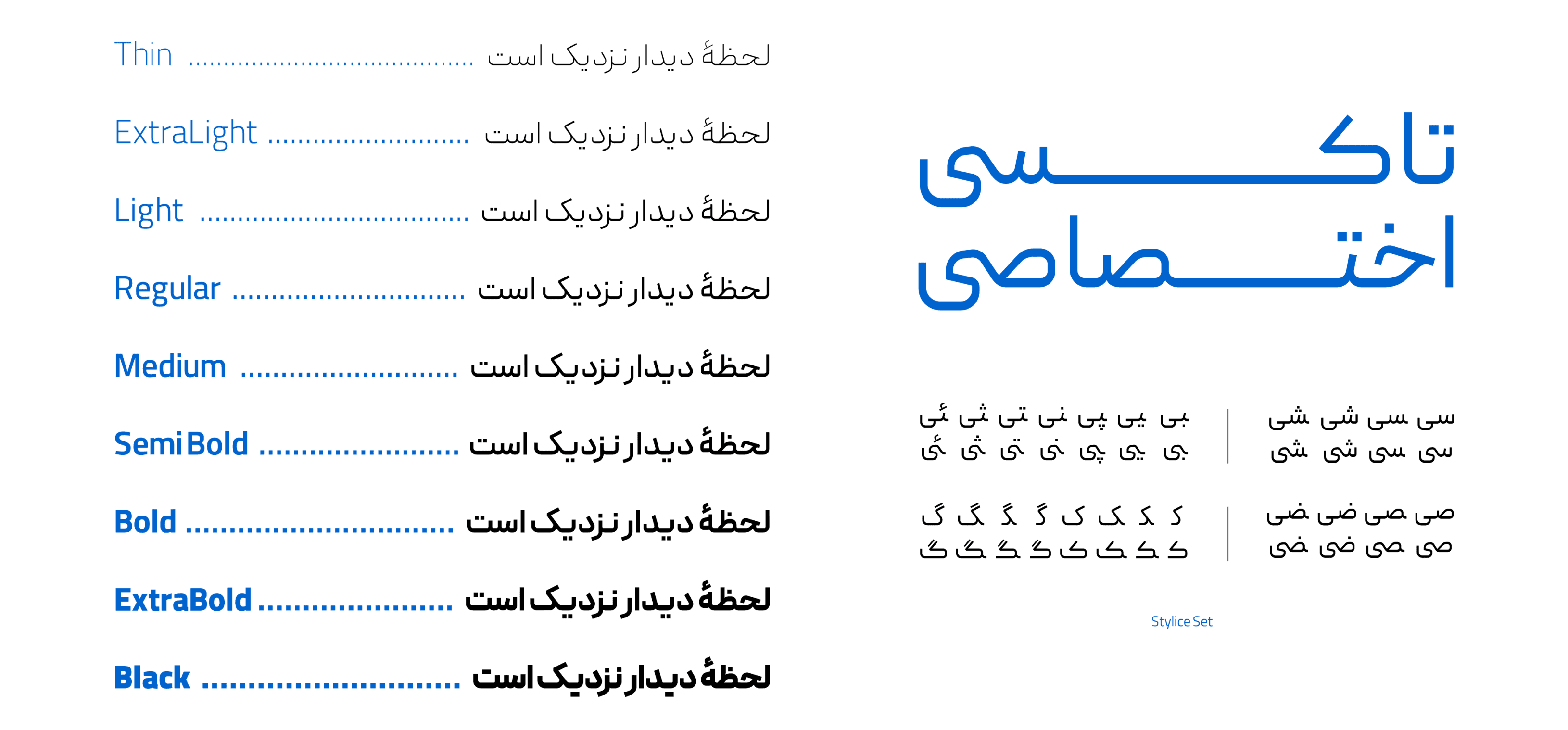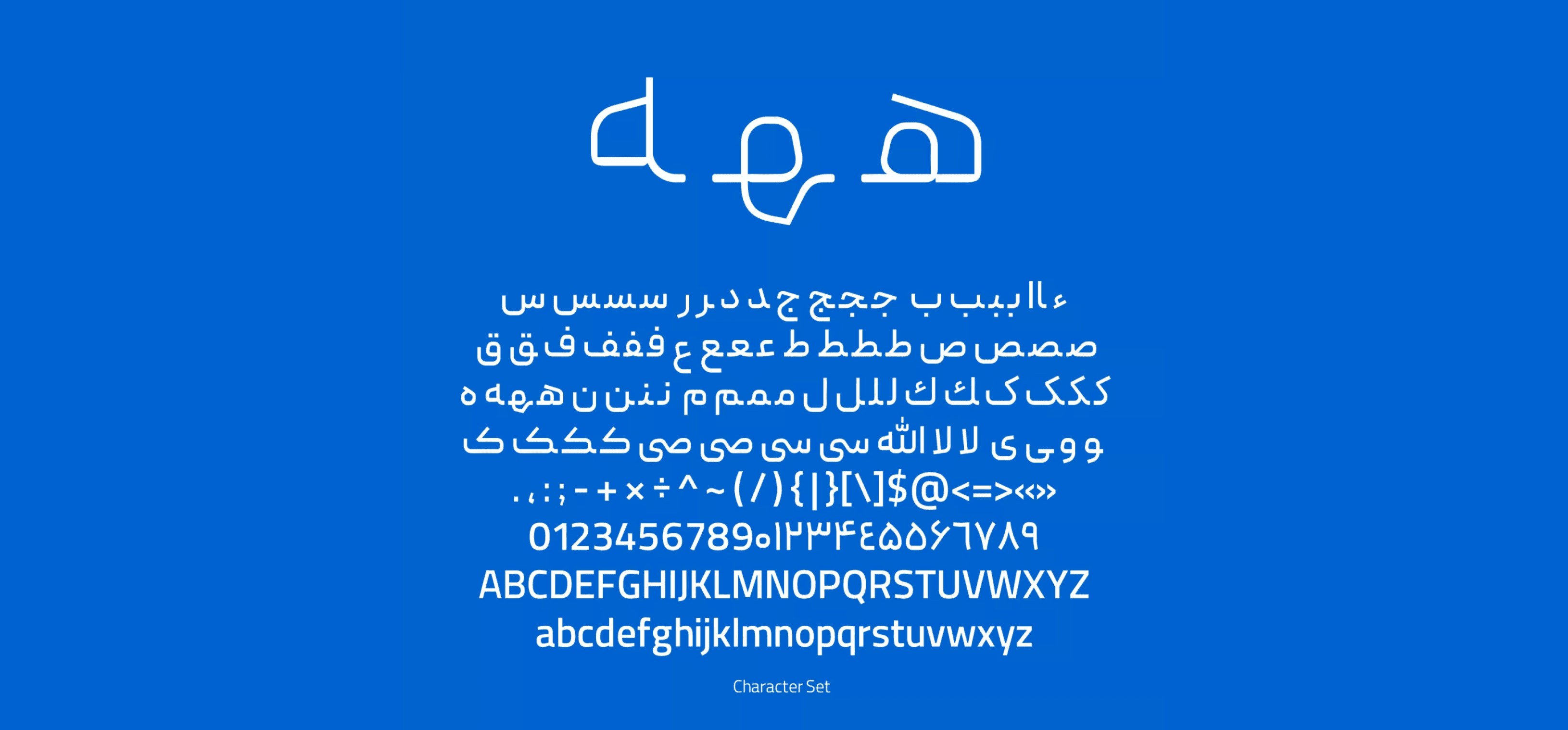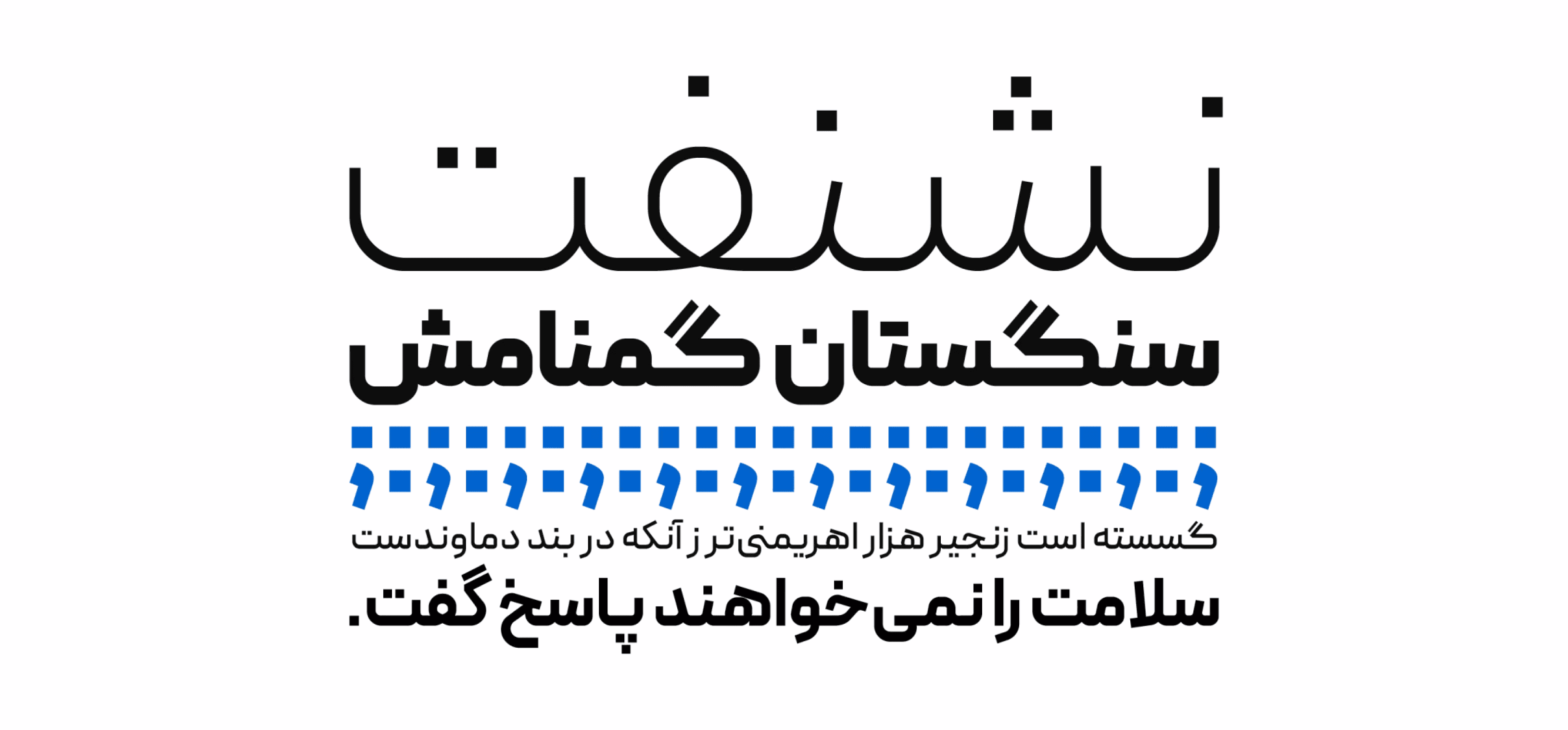
خط پیدا يتميّز ببنية هندسية، مع احتفاظه ببعض خصائص الخطوط التقليدية مثل النسخ.
المصمم ناصر خادم هو نفسه مبتكر خط كلمه، الذي حاز على شعبية واسعة في وقت قصير بعد إطلاقه، خاصة في مجالات التصميم التجاري وصناعة المحتوى الرقمي.
خط پیدا يستلهم من جمالية "كلمه" من حيث البنية الهندسية، وانخفاض التباين في السماكة، والأشكال المبتكرة للحروف، لكنه يتفوّق عليه بفضل عائلة خطوط أكثر اكتمالاً، ودرجة أعلى من الوضوح، مما يجعله أكثر ملاءمة للنصوص الطويلة والاستخدامات القرائية.